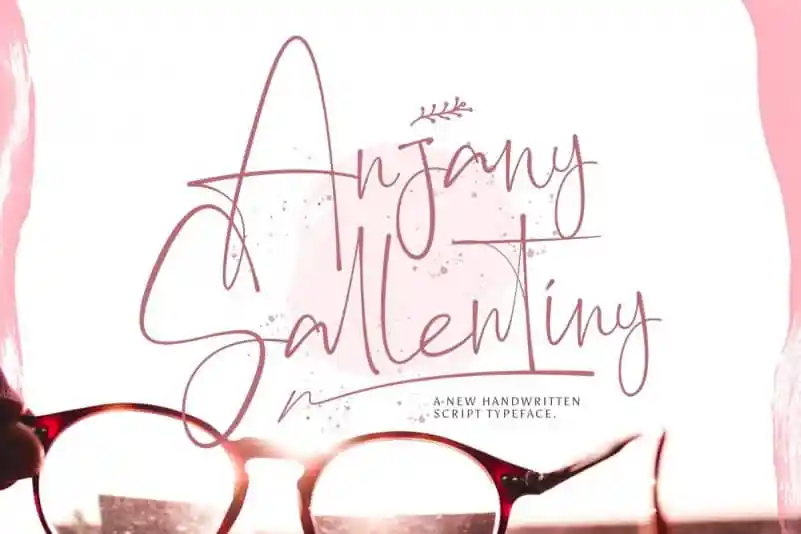
Anjany Sallentiny Script Font – Fonte Grátis
Anjany Sallentiny Script Font – Download Grátis
Anjany Sallentiny Script Font
A Anjany Sallentiny Script Font é uma seleção de letras curvilíneas que traz a essência do romance e da delicadeza. Ela foi criada pela StringLabs, uma produtora conhecida no mundo dos materiais gráficos digitais. Com seu equilíbrio perfeito entre as letras e um desenho leve e suave, esta fonte se destaca como ideal para designers de ideias extremamente criativas, trazendo vida a seus projetos mais audaciosos. Seja você uma designer de logomarca, um profissional gráfico ou mesmo um amante do design, o Anjany Sallentiny Script Font é uma escolha perfeita que vai enriquecer qualquer projeto com seu charme sofisticado e elegância romântica.